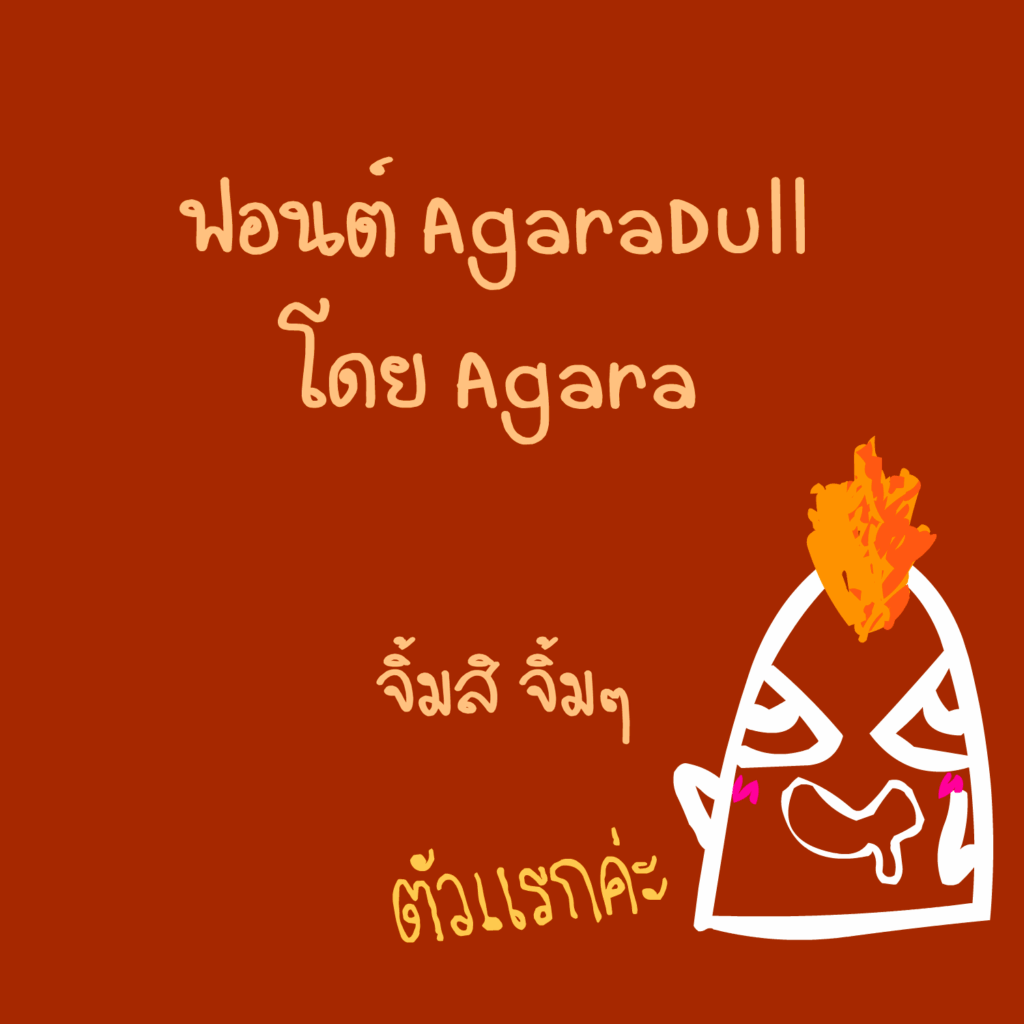
เสร็จแล้วค่ะ หลังจากอู้มาตั้งแต่สมัยพระเจ้าเหา
;;heart;; จะกลายเป็น ♥
;;david;; จะกลายเป็นดาวเดวิด
;;22;; จะกลายเป็นหน้ายิ้ม
จริงๆ แล้วในพรีวิวมันจะไม่ค่อยเหมือนตัวที่โหลดเท่าไหร่นะคะ
AgaraDull